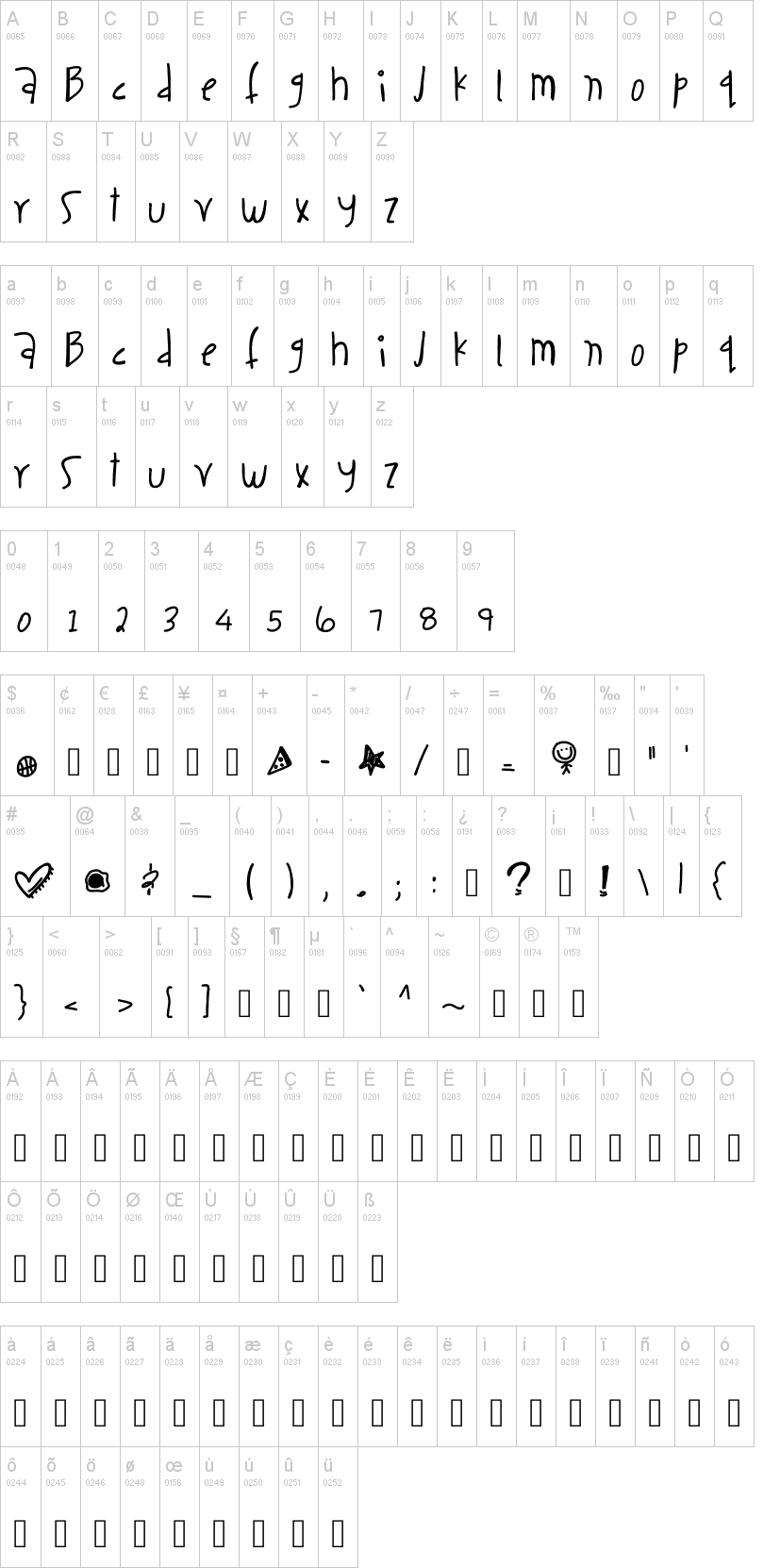
Case Addiction
Case Addiction 是一款由英国设计师 Dan Gretton 创作的一款自由版权字体。它是一款非常现代化的字体,具有良好的可读性和简洁的外观,可以满足用户的多种需求。它可以用于文字、标题、图标等,也可以用于品牌标识、印刷品、网站等各种项目。Case Addiction 字体具有轻松、活泼的感觉,可以提升任何设计项目的外观效果。
Case Addiction是一款非常不错的手写艺术字体,具有很好的视觉感,适合于文化类的宣传设计、商业类品牌的广告和产品包装设计以及个性化文字排版等较多场景。
Case Addiction字符映射图